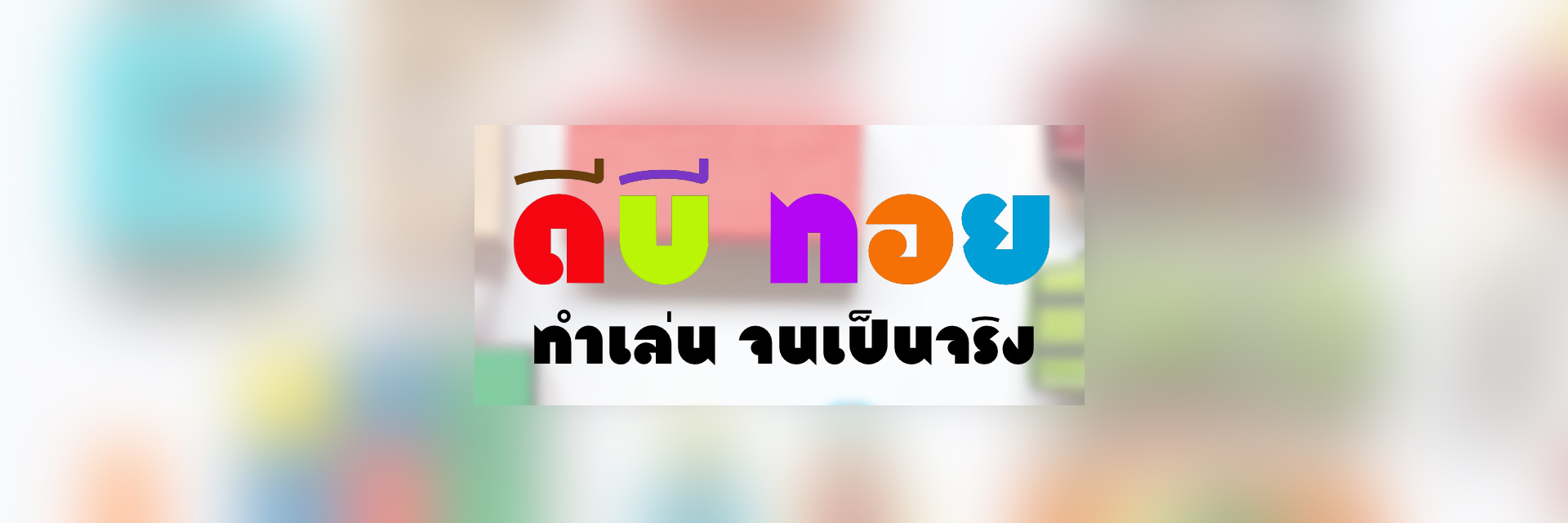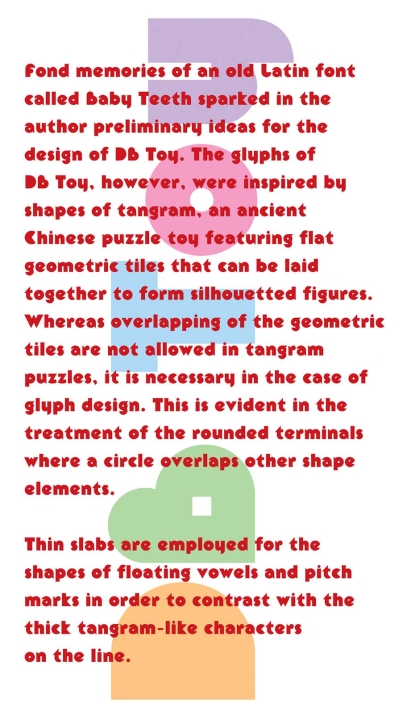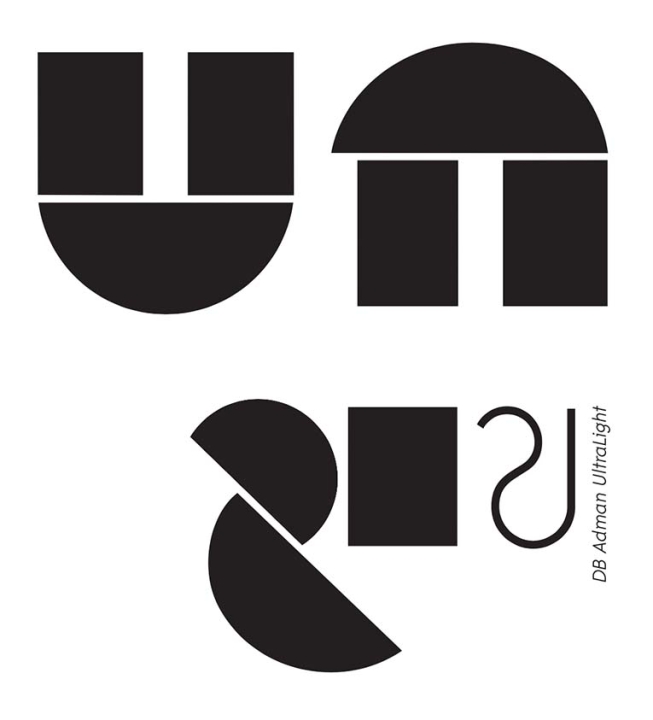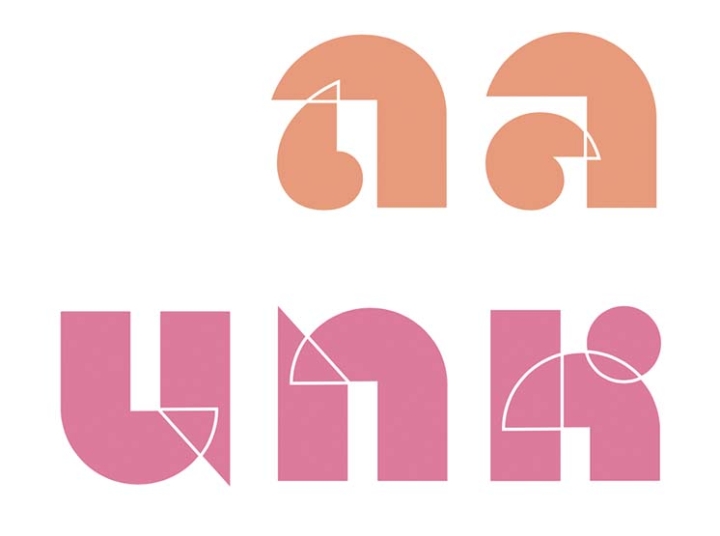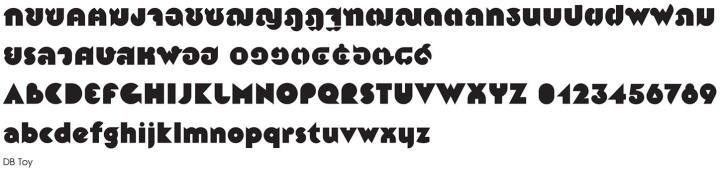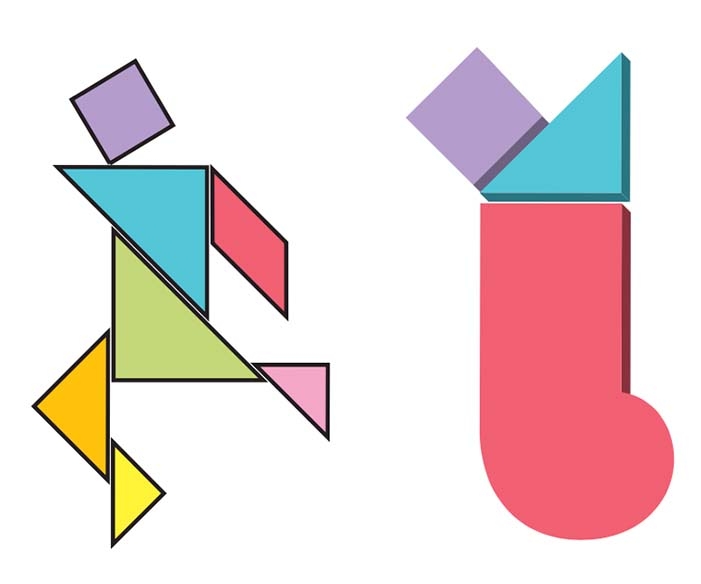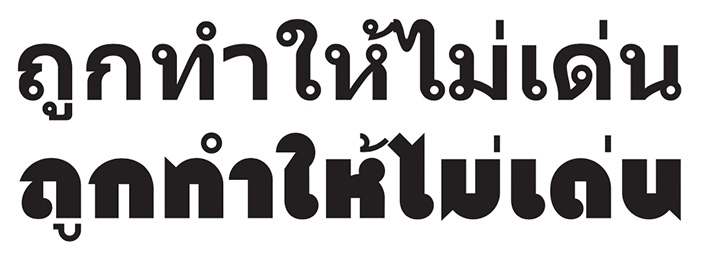
สาเหตุที่ฟอนต์ Extra Bold อย่าง DB Erawan ได้รับความนิยมอย่างมากน่าจะเป็นเพราะรูปทรงเรขาคณิตของมัน ประกอบกับมีความเป็น sans serif อยู่มาก เลยโดนใจนักออกแบบที่อยากให้งานดูทันสมัยแบบฝรั่ง! อย่างไรก็ตาม เมืองไทยก็ยังไม่มีฟอนต์ไทยทรงเรขาคณิตแบบหนาปึ้กในอารมณ์อื่นๆ ให้เลือกใช้มากนัก โดยเฉพาะที่ดูเป็นกันเองและเป็นไทยมากกว่า DB Erawan ขึ้นมาหน่อย. ผมจึงลองจับเอาแบบตัวอักษร Baby Teeth เท่าที่พอจําได้มาใส่ความเป็นไทยเข้าไปเพื่อเพิ่มทางเลือกใหม่ๆ ให้กับนักออกแบบไทย.
วิธีการของผมไม่มีอะไรมาก ข้อแรกคือไม่พยายามไปหาซื้อฟอนต์ Baby Teeth จาก myfonts.com หรือแม้แต่จะเปิดหาจากกองหนังสือเกี่ยวกับ Typeface (ซึ่งคาดว่าน่าจะเจอ) เพื่อที่ผมจะได้สลัดหนีความเป็นทาส Baby Teeth ไปเสียได้! ข้อสองคือใช้หลักการของเล่นประเภท Puzzle ของจีนที่ฝรั่งเรียก Tangram ลักษณะ เป็นชิ้นไม้รูปทรงเรขาคณิต 7 ชิ้น (ที่เกิดจากการซอยแบ่งจากชิ้นจัตุรัสใหญ่ด้วยเส้นแนวทะแยงเป็นหลัก) จะต่อเล่นเป็นรูปอะไรก็ได้แล้วแต่จะจินตนาการ. ฟอนต์ที่กําลังจะเกิดขึ้นใหม่ก็ใช้วิธีเดียวกันนี้
Tangram เกิดจากการแบ่งซอย แผ่นสี่เหลี่ยมจัตุรัสออกเป็น 7 ชิ้น
ผมร่างรูปทรงเรขาคณิตปะติดปะต่อกันอย่างสนุกมือ ทั้งสี่เหลี่ยม, สามเหลี่ยม, ทรงกลม ประกอบเข้าด้วยกันให้ดูเป็นตัวอักษรไทย. มีหลักว่ารูปทรงต่างๆ จะต้องมีด้านสัมผัสกันเพื่อเป็น silhouette ของตัวอักษร เหมือน silhouette ภาพของ Tangram ต่างกันตรงที่ไม่ถึงกับต้องใช้รูปทรงและจํานวนชิ้นตายตัวแบบ Tangram อีกทั้งยังอนุโลมให้วางทับซ้อนกันได้บ้างตามสมควรเพื่อผลทางการอ่าน เช่น ทรงกลมทึบเล็กๆ ที่ใช้แทนหัวของอักษร เป็นต้น.
บ และ ก คืออักษร 2 ตัวที่เป็นพื้นฐานที่สุด. บ ประกอบขึ้นจากสี่เหลี่ยมผืนผ้า 2 แท่ง วางสัมผัสปลายเส้นฐานล่างรูปครึ่งทรงกลม. ส่วนตัว ก เหมือน บ กลับด้าน เพียงแต่ให้ขาหน้าเลื่อนเข้ากลางเล็กน้อยเพื่อให้ส่วนบน ที่ล้ำออกไปดูเป็นปากอักษร ก.
ตัว ข (รวมทั้ง ช) ใช้ประสบการณ์เพิ่มจากตัว ข ที่เป็นตัวเก่งของ DB Adman มาประกอบขึ้นใหม่ด้วยครึ่งทรงกลมทึบ 2 ขนาดแทนการขมวดม้วนของหัวเข้ากับเส้นหน้า. ตัว ย ซึ่งซับซ้อนกว่านั้นได้รับอิทธิพลมาจากตัว ข โดยตรง.
ตัว ค นั้นยอมให้หัวกลมทึบทับขาหน้าเล็กน้อย เพื่อดูออกได้ง่ายว่าเป็นหัวที่ยื่นออกมาจากขาหน้า เมื่อมันถูกเติมหางทะแยงแหลมขึ้นไปจึงได้ตัว ศ ที่มีหน้าตาดูเหมือนมนุษย์ค้างคาวที่มีหูข้างเดียว!
ตัว น, ม เมื่อลองเขียนวงกลมทั้งหัวและขมวดม้วนดู ปรากฏว่าดูคล้ายกันมาก เลยลองใช้เส้นทะแยงเป็นรูปสามเหลี่ยมแหลมลงมาเป็นขมวดม้วนดู (คล้ายหาง ศ) พบว่าแยกแยะกันได้ดีแถมรูปทรงน่าสนใจกว่า. ส่วนหัว ตัว ห นั้นไม่จําเป็นต้องแหลมแบบตัว ท (ซึ่งเป็นผลต่อเนื่องมาจากตัว น) แค่เพิ่มทรงกลมแทนขมวดม้วนก็ชวนมองแล้ว.
หัวตัว ล ถูกพลิกหมุนทวนเข็มนาฬิกา 90 องศา เพื่อทําหัวตัว ถ ที่ดูห่างไกลจากตัว ด แล้วพลิกกลับมา เป็นตัว ภ.
ตัว พ ฟ นั้นเลี่ยงใช้เส้นหน้า, กลาง, หลัง แบบตั้งตรง (ซึ่งจะทําให้ดูอ้วนมาก) มาเป็นแบบหยักฟันปลา แล้วใส่หัวกลมเข้าไปให้มันดูต่างจากตัว W. เช่นเดียวกับที่ใส่หัวกลมให้ตัว ร เพื่อไม่ให้มันเป็น S จ๋าแบบฝรั่ง. จะเห็นได้ว่าการใส่หัวกลมเพื่อให้ดูเป็นไทยนั้นต้องใช้สติไม่หุนหันไปตามอําเภอใจ เช่น ตัว บ ขืนใส่หัวเข้าไปอาจไขว้เขวเป็น ตัว ข เอาได้.
สระ ใ, โ เหมือนมี Packman มาวางอยู่บนสระ เ. ส่วนสระ ไ ดูให้ดีที่เกิดจากต่อด้านบนสระ เ ขึ้นไปด้วยรูปสามเหลี่ยม แล้วเอารูปสี่เหลี่ยมเล็กๆ วางสัมผัสด้านทะแยงคล้ายบางอารมณ์ของ Tangram ที่ผมซึมซับมา.
ฟอนต์ Tahoma Bold และ DB Toy รูปสระบน-ล่าง, วรรณยุกต์, การันต์ ฯลฯ ถูกทําให้ไม่เด่น ด้วยน้ําหนักเส้นสม่ำเสมอแบบค่อนข้างบาง
ถ้าสังเกตดูให้ดี ชุดตัวอักษรไทยที่ประกอบขึ้นด้วย 2 ขา จะมีพื้นที่ว่างปรากฏเป็นมุมฉากซ่อนอยู่เสมอ ซึ่งยึดโยงมาจากตัวพื้นฐาน บ และ ก ที่กล่าวมาแต่ตอนต้นนั่นเอง. ลักษณะพิเศษนี้ได้ตกทอดไปสู่อักษรละตินในชุดของมันด้วยและน่าจะทําให้มันดูต่างไปจาก Baby Teeth พอสมควรเลยทีเดียว.
จุดเด่นอีกประการหนึ่งของฟอนต์ชุดนี้ คือ รูปสระ บน-ล่าง, วรรณยุกต์, การันต์ ฯลฯ ถูกทําให้ไม่เด่น ด้วยน้ําหนักเส้นสม่ำเสมอแบบค่อนข้างบาง เพื่อเปิดโอกาสให้อักษรขี้เล่นในร่างอ้วนทึบได้อวดตัวเองอย่างเต็มที่. อันที่จริงแล้วเป็นวิธีการที่เคยมีคนนํามาใช้ออกแบบฟอนต์ ไทยชื่อ Tahoma มาก่อน เพื่อแก้ปัญหาพื้นที่ด้านบนที่มีอยู่น้อย (เพราะถูกออกแบบให้ใช้ร่วมกับตัวละตินของมัน ซึ่งมีพื้นที่บนแคบกว่าฟอนต์ไทยปรกติ) Tahoma ที่ใช้กันแพร่หลายใน web อาจดูขัดหูขัดตาไปบ้างสําหรับการเป็นตัวเนื้อไทยเล็กๆ แต่สําหรับการพลิกมาใช้กับฟอนต์ดีสเพลย์ไทยเยี่ยงนี้ ผมเชื่อว่าน่าจะเป็นการท้าทายที่ให้ผลตอบรับคุ้มค่า.
ผมตั้งชื่อให้มันว่า DB Toy เพื่อบันทึกอารมณ์สนุกสนานตลอดการทํางานจนผลลัพธ์ออกมาก็ยังดูสนุกเหมือนต่อชิ้น Tangram ทั้ง 7 เป็นรูปร่างตามแต่จินตนาการ. Tangram ได้รับการยอมรับในแง่ศิลปะว่า ช่วยให้เด็กๆ จินตนาการต่อเติมรูปทรงธรรมชาติได้จากรูปทรงเรขาคณิตอย่างอิสระ. เมื่อรูปทรงถูกต่อเติมออกไปมากแบบขึ้น แล้วบันทึกไว้แต่เส้น Outline ให้ผู้อื่นลองพยายามทําตามให้ได้บ้าง จึงกลายเป็น Puzzle ซึ่งสนุก เฉพาะกับคนที่ชอบเกมท้าทายปัญญาเท่านั้น.
ถึง DB Toy จะทําออกมาอย่างเล่นๆ แต่จะเห็นได้ว่าผมกลับเป็นจริงเป็นจังมากในเรื่องการทําอย่างไรให้อ่านง่ายเข้าไว้ ทําไมน่ะหรือ?
ก็เพราะมันชื่อ DB Toy ไม่ใช่ DB Puzzle ให้ต้องมานั่งเดาให้เมื่อยเซลสมองว่ามันตัวอะไรกันวะ?!?